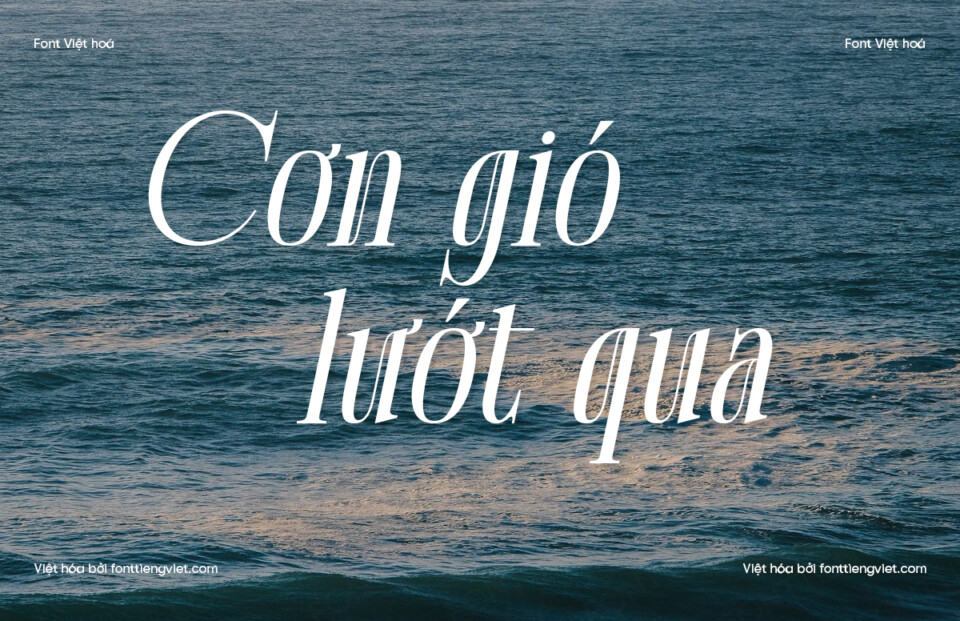
Tải Ngay Font Việt hóa 1FTV VIP Astrite Linery Italic Đẳng Cấp Cho Thiết Kế
Giới thiệu về Font Việt hóa 1FTV VIP Astrite Linery Italic
Trong thế giới đồ họa hiện đại, việc lựa chọn một bộ Font Miễn Phí chất lượng luôn là ưu tiên hàng đầu của các nhà thiết kế. Đặc biệt, bộ Font Việt hóa 1FTV VIP Astrite Linery Italic nổi lên như một hiện tượng nhờ sự kết hợp hoàn hảo giữa nét chữ thanh mảnh và độ nghiêng tinh tế. Đây là phiên bản được tinh chỉnh kỹ lưỡng về dấu tiếng Việt, giúp người dùng tại Việt Nam dễ dàng ứng dụng vào các dự án truyền thông mà không lo lỗi hiển thị. Phong cách Italic đặc trưng của bộ phông này mang lại cảm giác chuyển động, mềm mại nhưng vẫn giữ được sự chuyên nghiệp cần thiết.
Đặc điểm nổi bật của Font Việt hóa 1FTV VIP Astrite Linery Italic
Điểm làm nên sự khác biệt của Font Việt hóa 1FTV VIP Astrite Linery Italic chính là những đường nét hình học được cách điệu theo hướng nghệ thuật đương đại. Các ký tự có cấu trúc đồng nhất, tạo nên sự cân bằng tuyệt đối cho văn bản. Khi sử dụng bộ chữ này, bạn sẽ nhận thấy các đường nối giữa các con chữ rất mượt mà, gợi liên tưởng đến những nét vẽ tay điêu luyện. Đối với các bạn học sinh hay thầy cô giáo đang tìm kiếm một công cụ hỗ trợ làm bài thuyết trình hoặc thiết kế thiệp mời, đây chắc chắn là một sự lựa chọn không thể bỏ qua vì tính ứng dụng cực cao và vẻ ngoài bắt mắt.
Ứng dụng thực tế của Font Việt hóa 1FTV VIP Astrite Linery Italic
Nhờ vẻ ngoài sang trọng và thanh lịch, Font Việt hóa 1FTV VIP Astrite Linery Italic thường xuyên được xuất hiện trong các bộ nhận diện thương hiệu cao cấp. Từ việc thiết kế logo cho đến làm bìa sách, bộ font này luôn chứng minh được giá trị thẩm mỹ của mình. Trong môi trường học đường, các bạn có thể dùng nó để trang trí tiêu đề báo tường hoặc làm nổi bật các ý chính trong bài giảng điện tử. Sự thanh thoát của kiểu chữ nghiêng giúp người xem không bị mỏi mắt, đồng thời tạo ra một nhịp điệu đọc rất tự nhiên và lôi cuốn.
Lưu ý khi sử dụng Font Việt hóa 1FTV VIP Astrite Linery Italic trong thiết kế
Mặc dù Font Việt hóa 1FTV VIP Astrite Linery Italic rất đẹp nhưng người dùng cần lưu ý về kích thước văn bản. Để đảm bảo tính thẩm mỹ cao nhất, bạn nên sử dụng phông chữ này cho các đoạn tiêu đề ngắn hoặc các câu trích dẫn mang tính nhấn mạnh. Tránh sử dụng cho các đoạn văn bản dài hàng nghìn chữ vì độ nghiêng đặc trưng có thể làm giảm khả năng đọc nhanh. Ngoài ra, việc kết hợp bộ font này với một font chữ không chân (Sans-serif) đơn giản sẽ tạo ra một bố cục hài hòa và chuyên nghiệp hơn rất nhiều cho tác phẩm của bạn.